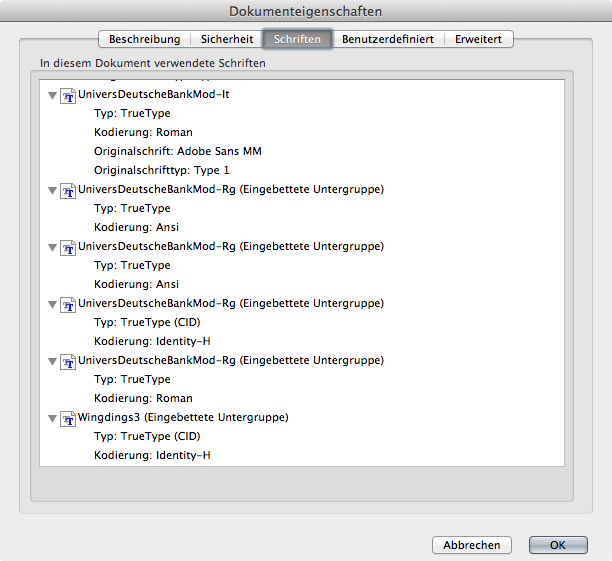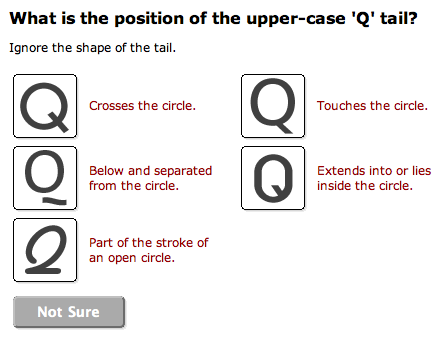
Schriften erkennen - die 10 besten Tricks
»Schrift gesucht« – ein Klassiker in allen Grafikdesigner-Foren. Man hat in einer Anzeige oder in einem Magazin eine tolle Schriftanwendung gesehen und möchte nun wissen, um welche Schrift es sich handelt. Oder man hat einen neuen Kunden, der seine eigene Hausschrift nicht kennt und als Muster lediglich einen alten Briefbogen vorlegt. Auch alte Hasen im Grafikdesign-Geschäft können nicht jede Schrift kennen. Doch es gibt eigene Tricks um die Suche leichter zu machen. Hier die 10 besten …
Trick № 1: WhatTheFont
Ein bekannter und beliebter Dienst zum Erkennen von kommerziellen Schriften ist WhatTheFont von MyFonts. Laden Sie eine Grafik mit dem Schriftmuster hoch und das System ermittelt aus dem riesigen MyFonts-Katalog mit derzeit circa 900 Schriftanbietern die passenden Schriften.
Der Dienst funktioniert dann am besten, wenn die Schriftmuster kontrastreich und unverzerrt sind und sich Buchstaben nicht miteinander oder mit Hintergrundbildern überlagern. Oft lohnt es sich deshalb, das Bild vorher in einem Bildbearbeitungsprogramm kurz entsprechend zu bereinigen.
Trick № 2: What Font is
Ein ganz ähnlicher Dienst wie WhatTheFont ist What Font is. Im Gegensatz zu ersterem liegt der Fokus hier auf kostenlosen Schriften. War man bei WhatTheFont nicht erfolgreich, lohnt daher oft ein zweiter Versuch bei What Font is.
Trick № 3: Der PDF-Trick
Sie wüssten gern, welche Hausschrift ein bestimmtes Unternehmen benutzt? Eine sehr sichere Methode, verwendete Schriften zweifelsfrei zu bestimmten, ist das Nachschauen in PDF-Dateien. Die Schriften sind hier in der Regel eingebettet und Anzeige-Programme wie der Adobe Reader gestatten eine Übersicht, welche Schriften in einem PDF verwendet werden.
Falls Sie noch kein PDF vorliegen haben, empfiehlt es sich, die Homepage des Herstellers nach PDFs zu durchsuchen. Bei Aktiengesellschaften sind zum Beispiel fast immer die Jahresberichte als PDFs hinterlegt.
Für eine gezielte Suche bei Google geben Sie zum Beispiel folgendes ein:
site:deutsche-bank.de .pdf
Noch genauer wird die Suche, wenn Sie für die Ergebnisse lediglich den Datei-Typ PDF zulassen:
site:deutsche-bank.de filetype:pdf
Laden Sie anschließend das PDF auf Ihren Rechner und öffnen Sie es im Adobe Reader. Öffnen Sie die Dokumenteigenschaften über   cmd   +   D   bzw.   STRG   +   D   und schauen Sie unter dem Reiter »Schriften« nach, welche Fonts in diesem PDF eingesetzt wurden. So lassen sich gegebenenfalls auch die Namen von Hausschriften zielsicher bestimmen, die von bestehenden Schriften abgeleitet wurden.
Trick № 4: Identifont – So ähnlich wie …
Nicht selten weiß man den Namen einer Schrift nicht, aber man kennt andere Schriften, die ganz ähnlich aussehen. Hier hilft die Identifont-Webseite. Einfach den Namen der bekannten Schrift eingeben und anschließend in der Seitenleiste die Vorschläge zu ähnlichen Schriften durchsuchen. Diese Auswahl wird von den Betreibern der Seite manuell gepflegt und ist dementsprechend treffsicher.
Trick № 5: Fragenkatalog
Identifont bieten noch eine weitere Möglichkeit, Schriften zu bestimmen. Über eine Serie von Fragen wie »Hat die Schrift Serifen?« oder »Ragt das J über die Grundlinie« wird die Schriftsuche immer weiter eingegrenzt, bis nur noch eine kleine Anzahl von Schriften infrage kommt. http://www.identifont.com/identify.html
Trick № 6: In meinen Schriften suchen …
Wenn man Schriften anhand einer Mustergrafik lediglich auf seinem eigenen Rechner suchen möchte, kann man dafür Programme wie Find my Font benutzen. Sie arbeiten nach dem gleichen Prinzip wie WhatTheFont und What Font is, aber durchsuchen dabei nur die Fonts auf der eigenen Festplatte. Wenn man nur mal schnell eine ähnliche Schrift zu einem Schriftmuster finden will, ohne dafür Geld auszugeben, findet man auf diese Weise leicht ein passende Schrift aus dem eigenen Schriftenbestand.
Trick № 7: Im Wiki nachschauen
Im Wiki von Typografie.info gibt es eine der größten Listen von Unternehmens-Hausschriften aus aller Welt. Die Liste kann von allen Typografie.info-Mitgliedern ergänzt oder abgeändert werden. Wir freuen uns über Deine Mithilfe, diese Liste aktuell und korrekt zu halten!
Trick № 8: »Wahrscheinlich isses Rotis!«
Auch wenn man heute theoretisch auf über 20.000 Schriftfamilien zurückgreifen kann – der Großteil der Schrifterkennungsanfragen in unserem Forum geht auf nur eine Handvoll Klassiker-Schriften zurück. Es lohnt sich also immer, diese zu kennen bzw. zuerst zu prüfen. Eine gute Übersicht dazu bietet zum Beispiel die Liste von FontShops 100 Besten Schriften.
Trick № 9: Plausibilitätsprüfung
Oft werden uns im Forum Schriftmuster zur Identifizierung vorgelegt, bei denen es sich gar nicht um gesetzte Schriften, sondern um eigenes gestaltete Schriftzüge (z.B. für Logos) handelt. Bevor man sich also auf die mühselige Suche nach der passenden Schrift macht, sollte man sich sicher sein, dass die Vorlage überhaupt aus einer heute verfügbaren Satzschrift besteht. Dazu ein paar Tipps:
Trick № 10: Die Profis fragen …